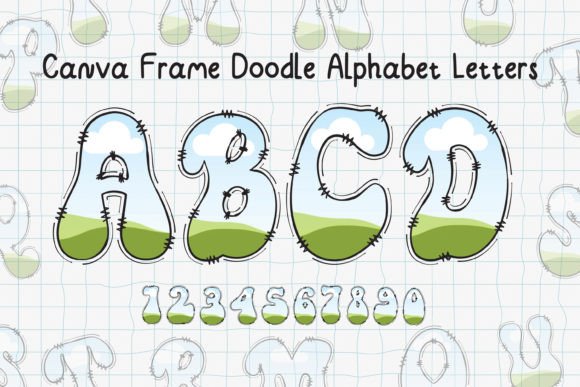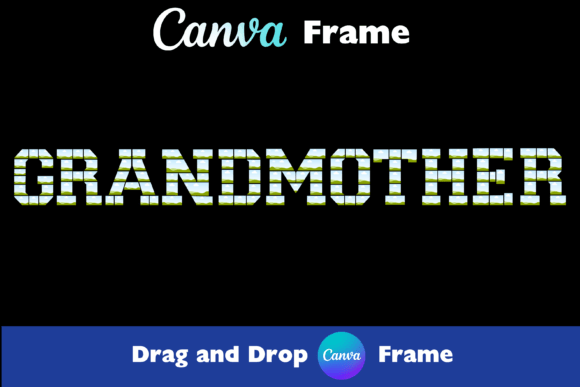
Custom Canva Alphabet Frames Fonts
Custom Canva Alphabet Frames Fonts์™€ ๊ฐ™์€ ๊ณ ํ’ˆ์งˆ ์ž์‚ฐ์„ ์ฐพ๊ณ  ์žˆ๋‹ค๋ฉด ์ด ํ”„๋ฆฌ๋ฏธ์—„ ํŒจํ‚ค์ง€๋Š” ์ฐฝ์˜์ ์ธ ํ”„๋กœ์ ํŠธ๋ฅผ ์œ„ํ•œ ํ™˜์ƒ์ ์ธ ์„ ํƒ์ž…๋‹ˆ๋‹ค.
์ •๋ฐ€ํ•˜๊ฒŒ ์ œ์ž‘๋œ Custom Canva Alphabet Frames Fonts๋Š” ๊น”๋”ํ•œ ๋ฒกํ„ฐ, ๋ถ€๋“œ๋Ÿฌ์šด ํƒ€์ดํฌ๊ทธ๋ž˜ํ”ผ ๋ฐ ์•ˆ์‹ฌํ•  ์ˆ˜ ์žˆ๋Š” ์ƒ์—…์šฉ ๋ผ์ด์„ ์Šค๋ฅผ ์ œ๊ณตํ•ฉ๋‹ˆ๋‹ค.
POD(์ฃผ๋ฌธํ˜• ์ธ์‡„) ์ œํ’ˆ, ๊ฒฐํ˜ผ์‹ ์ดˆ๋Œ€์žฅ ๋˜๋Š” ์†Œ์…œ ๋ฏธ๋””์–ด ๊ทธ๋ž˜ํ”ฝ์„ ๋งŒ๋“ค ๋•Œ Custom Canva Alphabet Frames Fonts๋Š” ์ด์ƒ์ ์ธ ์„ ํƒ์ž…๋‹ˆ๋‹ค.